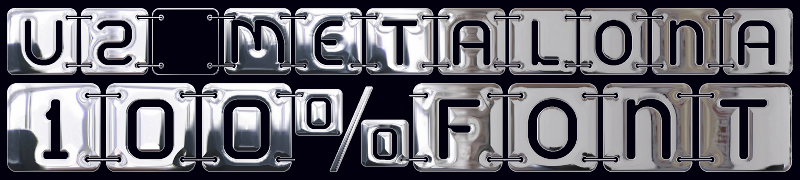
U2 Metalona*
Fuente decorativa que imita chapas unidas entre si.
Las letras propiamente dichas de esta tipografa pertenecen a la versin Unicase de mi tipografa llamada Sabtica.
La tipografa dispone de terminales para principio y final de frase, usa las teclas (<>), tambien los parntesis, los corchetes y las llaves son terminales.